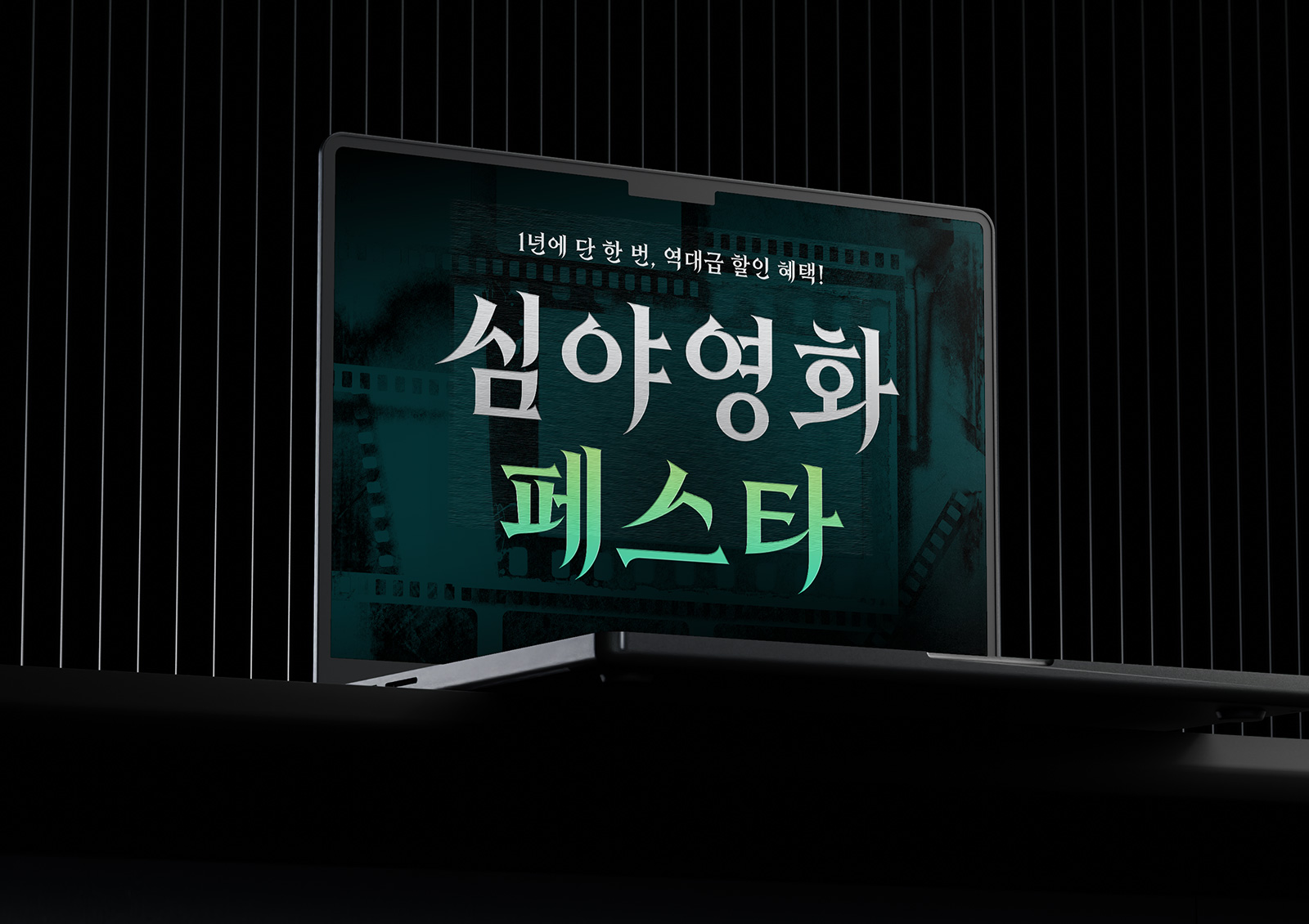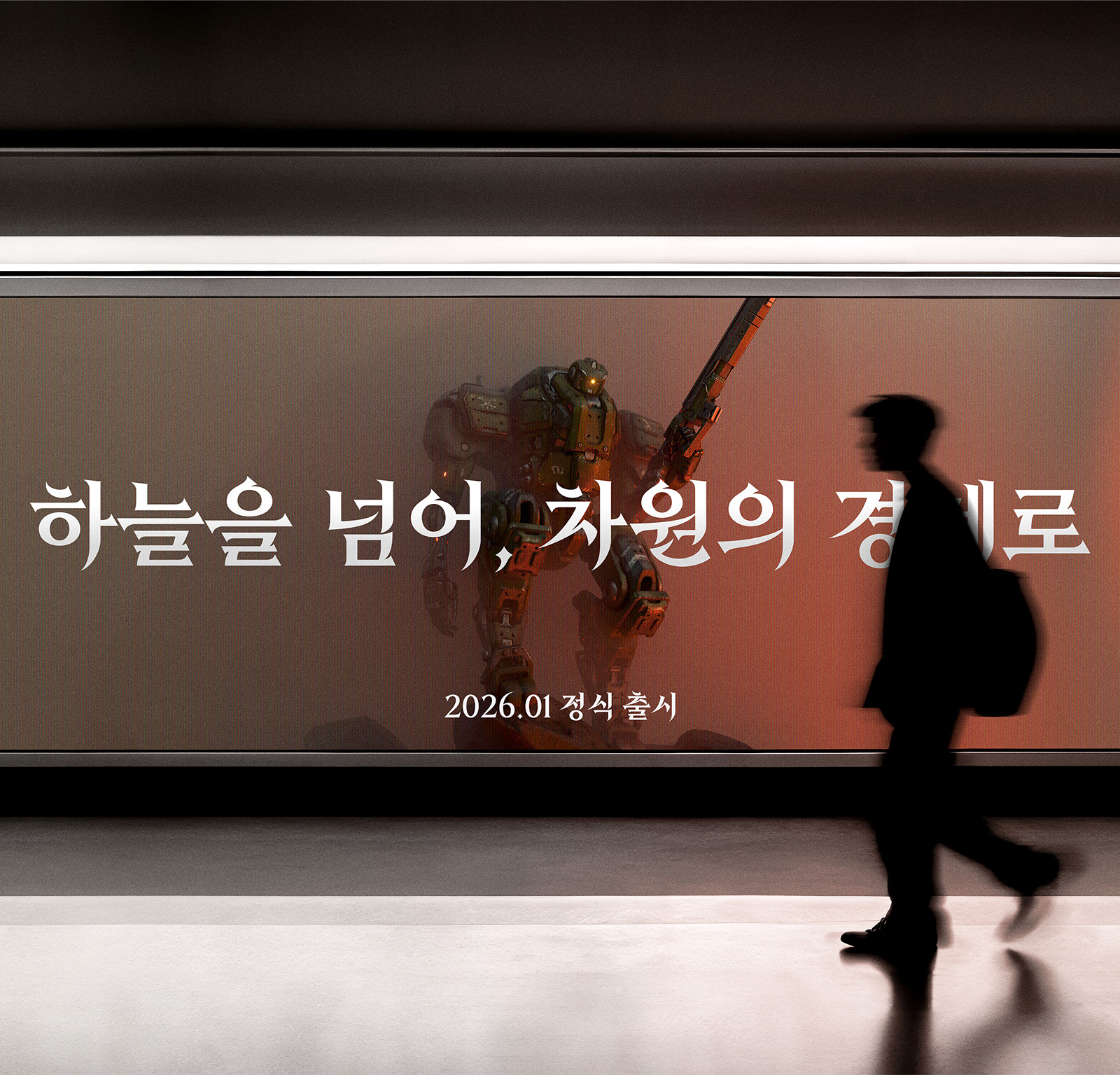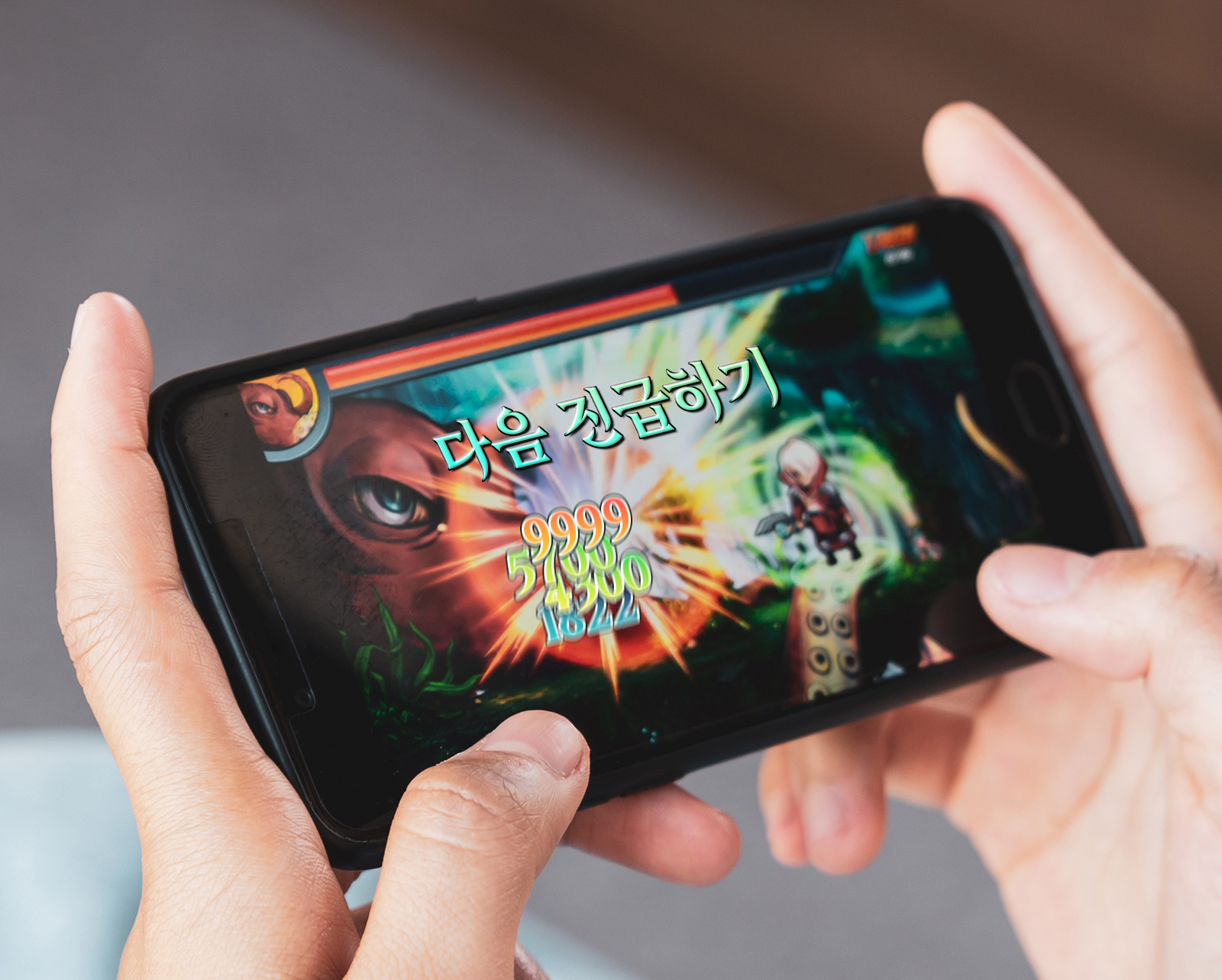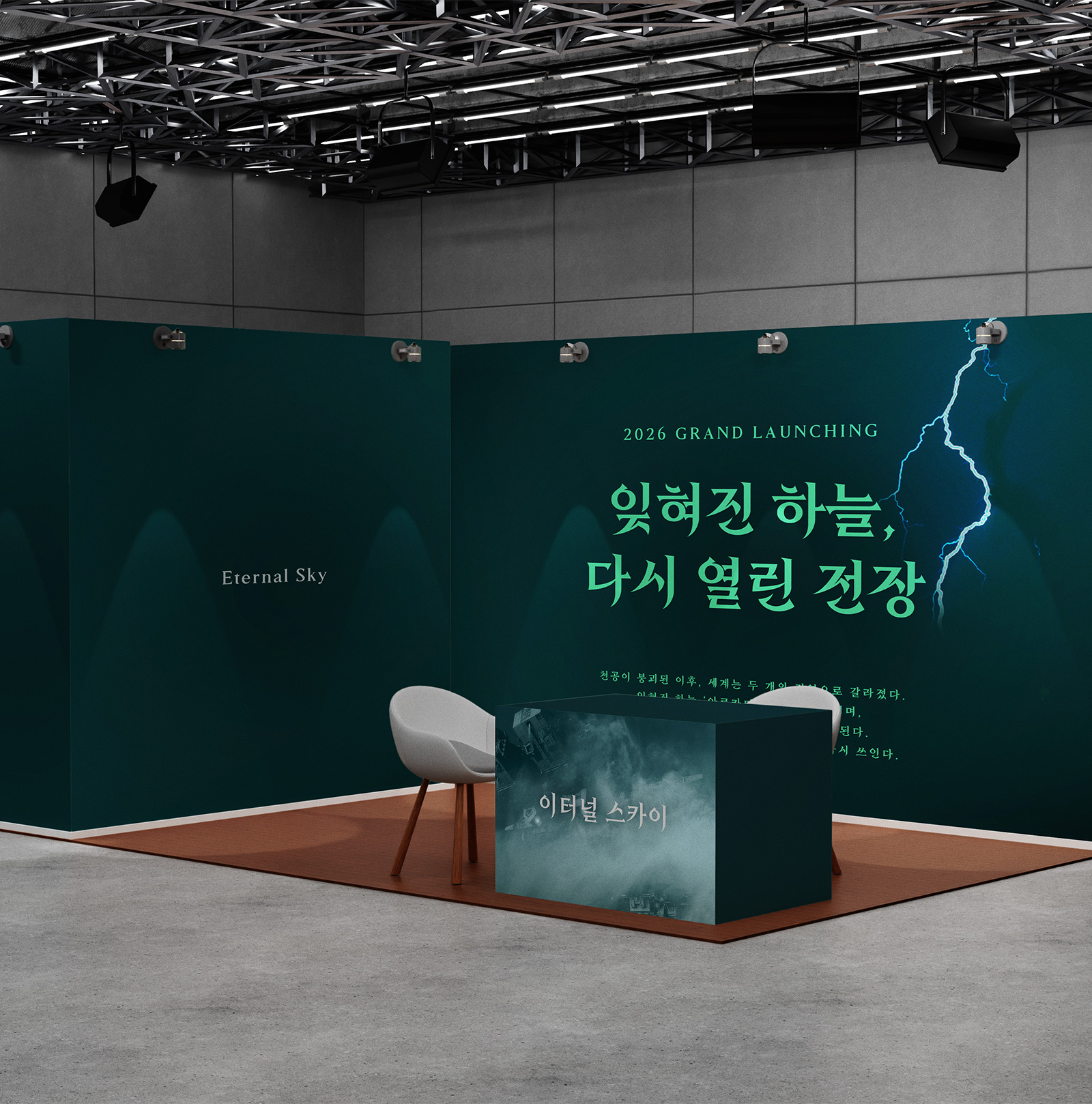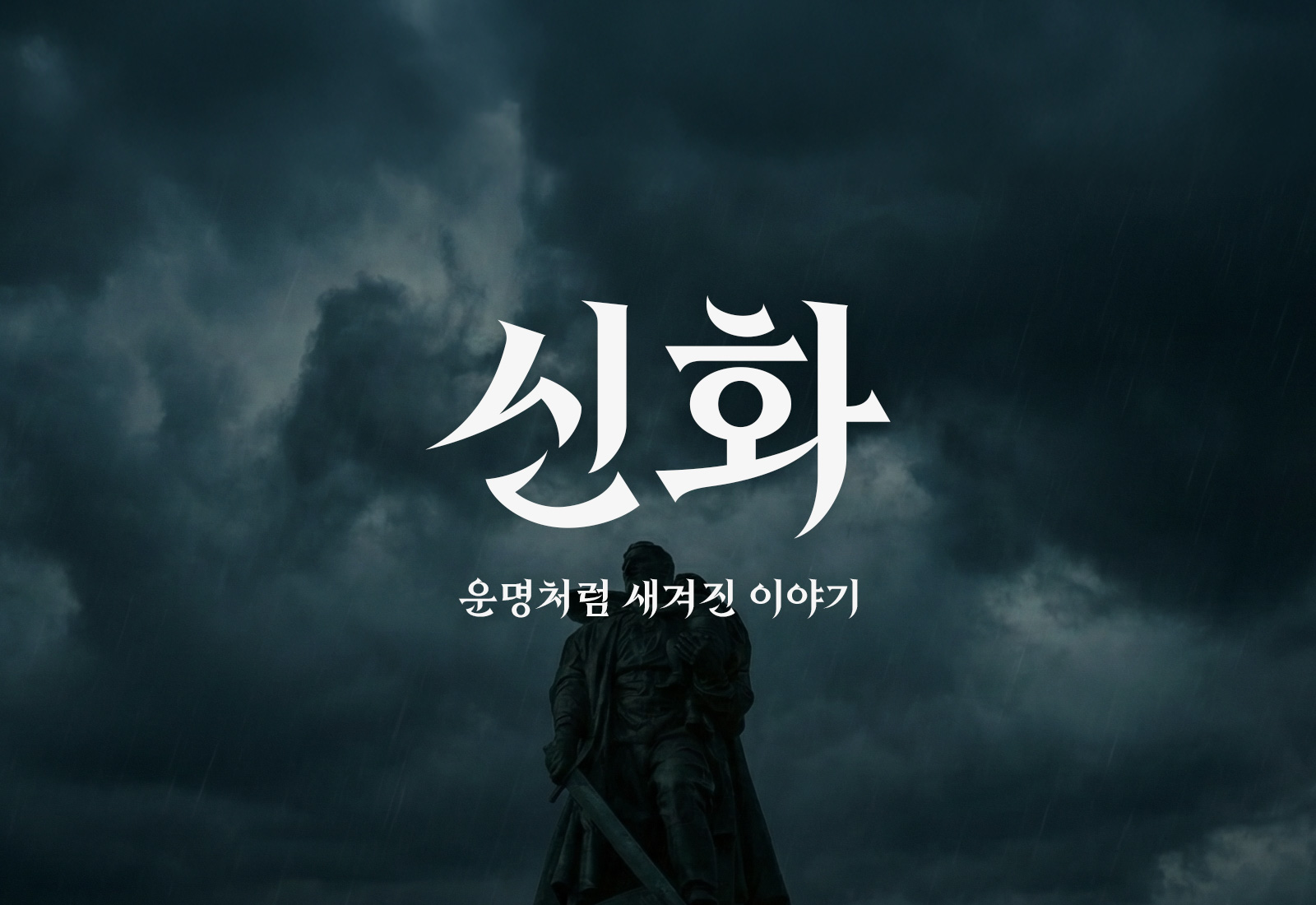
RixShinhwa
1 Style - RegularRix신화는 칼날처럼 정제된 선과 곡선의 균형이 어우러져,
단단한 긴장감과 서사적 무게를 지닌 제목용 헤드라인 서체입니다.
| FontFamily | Rix신화 / RixShinhwa |
| Design | Choi Beop-Ho |
| Direction | Park Yong-rak |
| Glyphs | 2,350 + 430 KR Characters / 94 Latin Characters / 986 Symbols |
- Regular
- 꽃처럼 피어나 별처럼 빛나는 그대에게